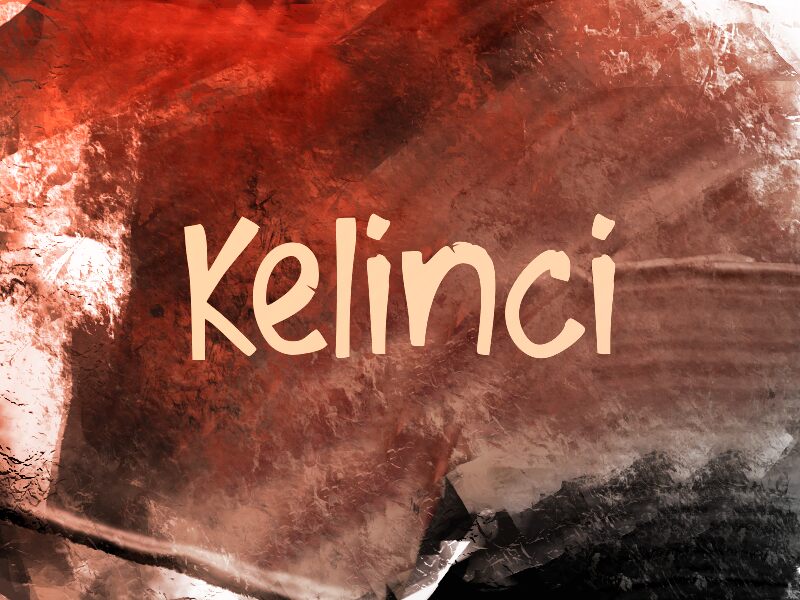
Kelinci di Wep è un font display gratuito in stile fumetto, caratterizzato da un tratto vivace, disegnato a mano e da quel ritmo irregolare tipico di una scrittura rapida. Le lettere puntano su tratti spessi, giunzioni strette e forme arrotondate e leggermente instabili, conferendo al font un’anima da fumetto informale, lontana dalla levigatezza artefatta dei cartoni animati.
È perfetto per poster giovanili, packaging giocosi, copertine di libri, insegne di bar e titoli per i social media, dove un font gratuito può mantenere vivo il design senza sembrare forzatamente carino. Poiché le lettere risultano alte, elastiche e un po' improvvisate, Kelinci dà il meglio di sé in titoli brevi, nomi e scritte d'impatto che cercano un tocco umano e rilassato.
Kelinci